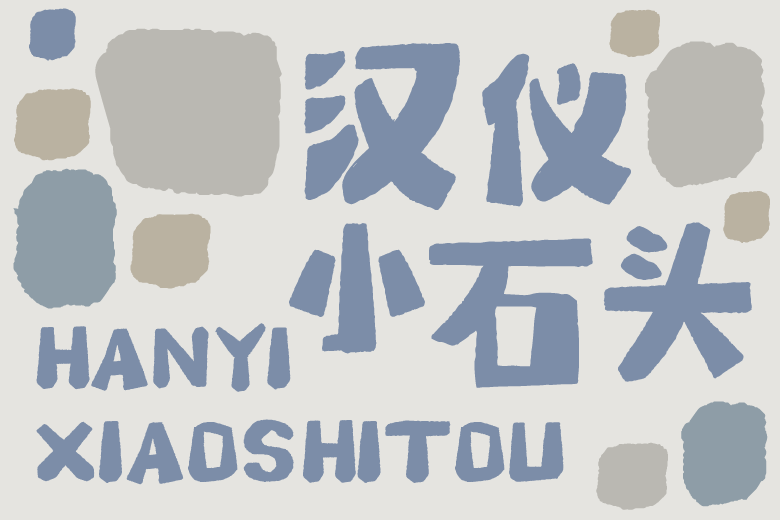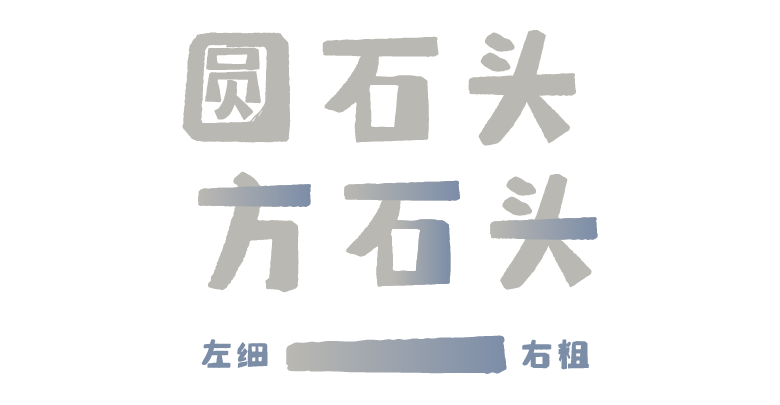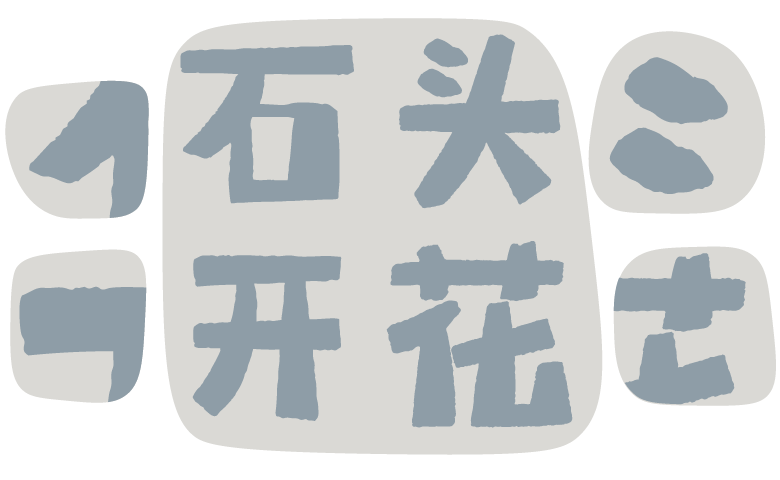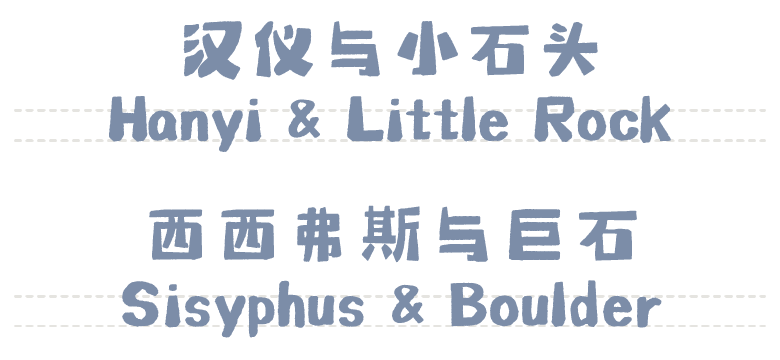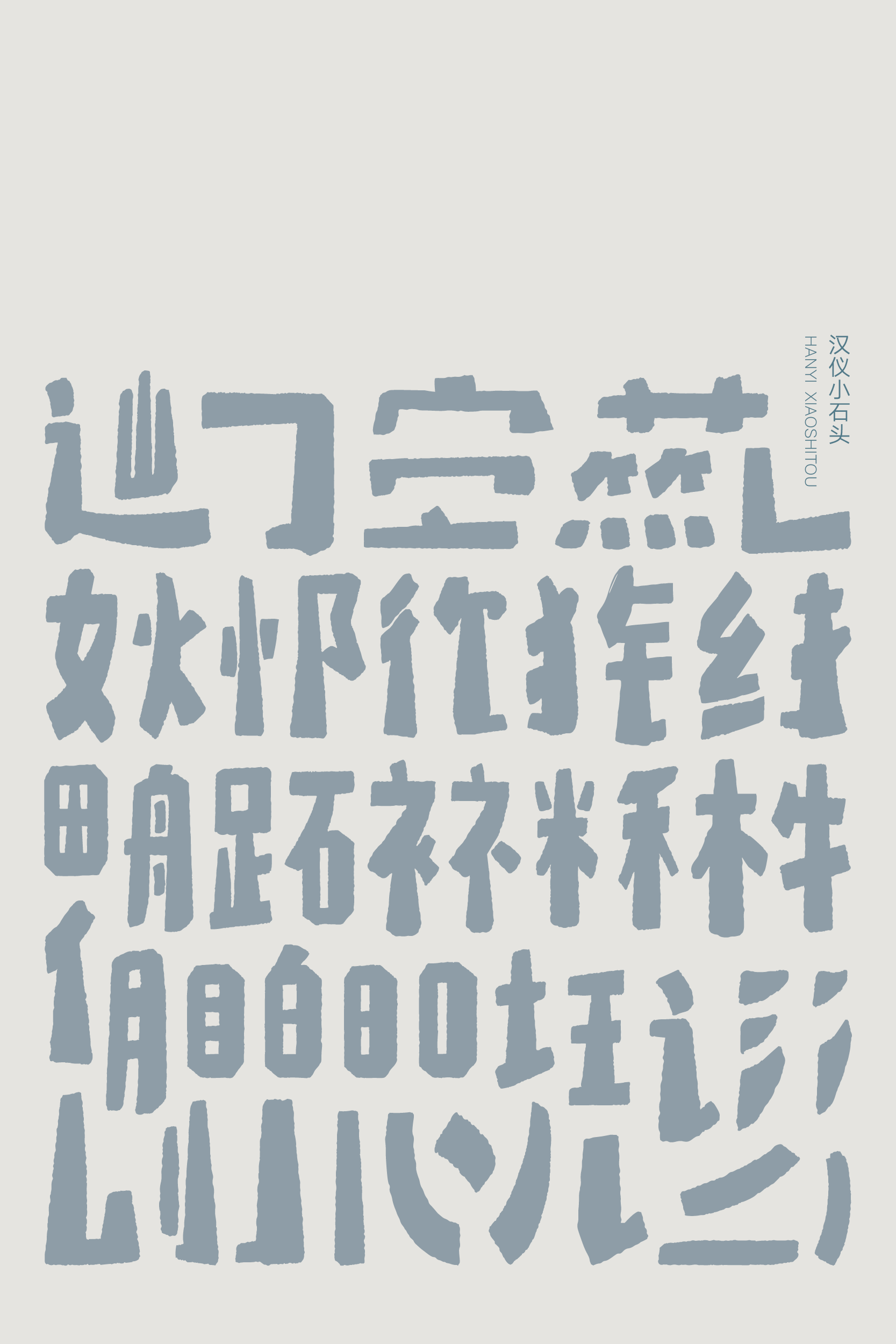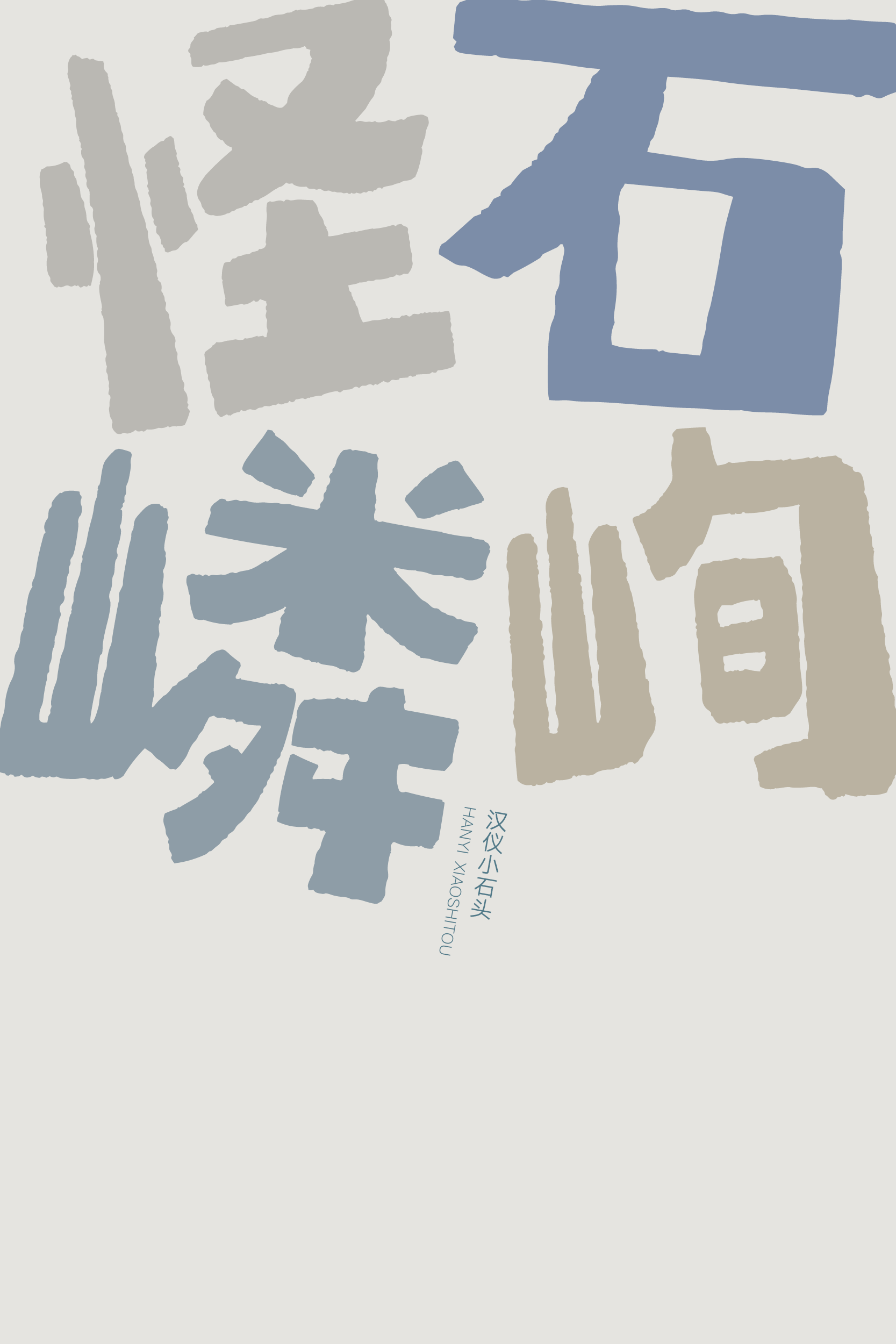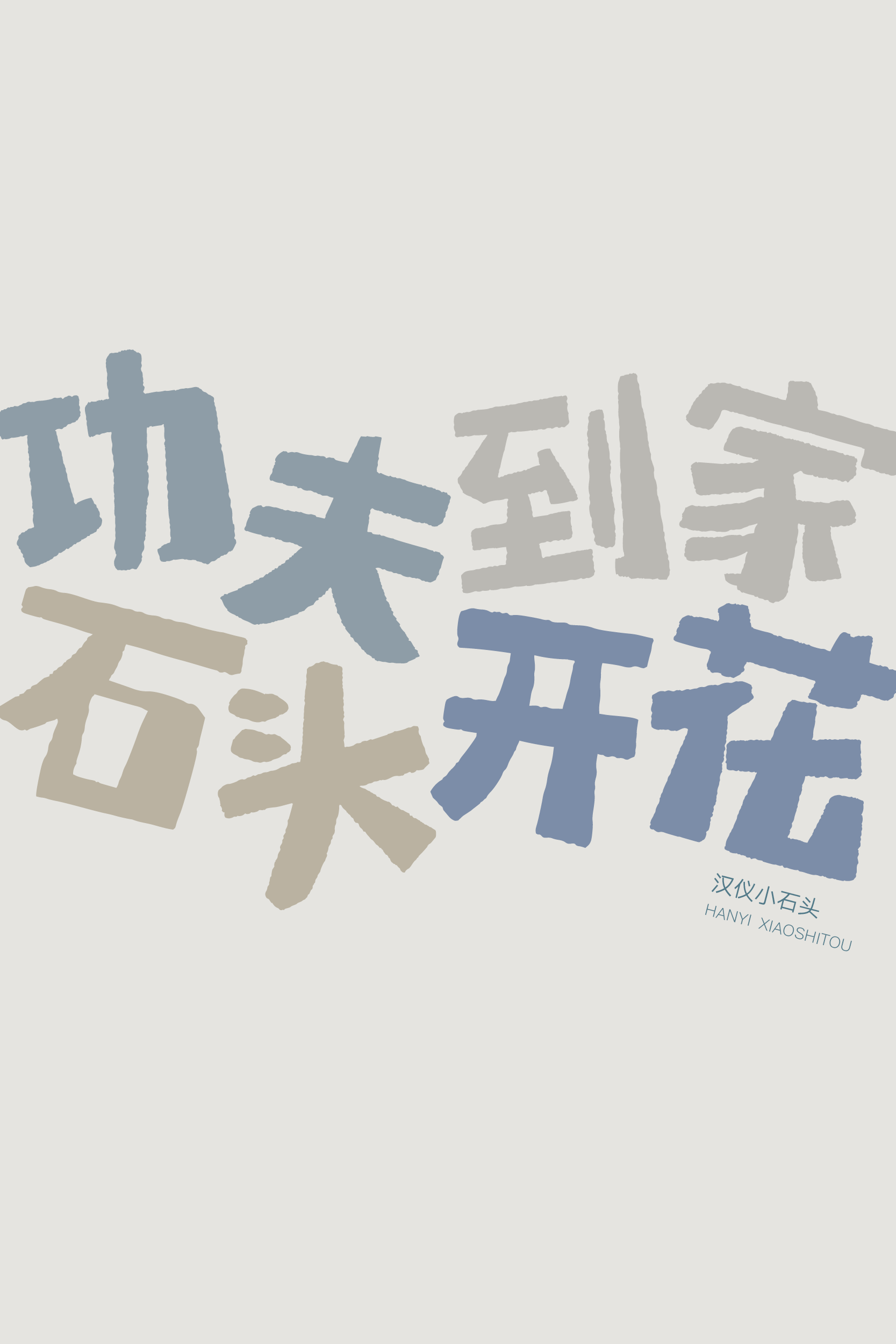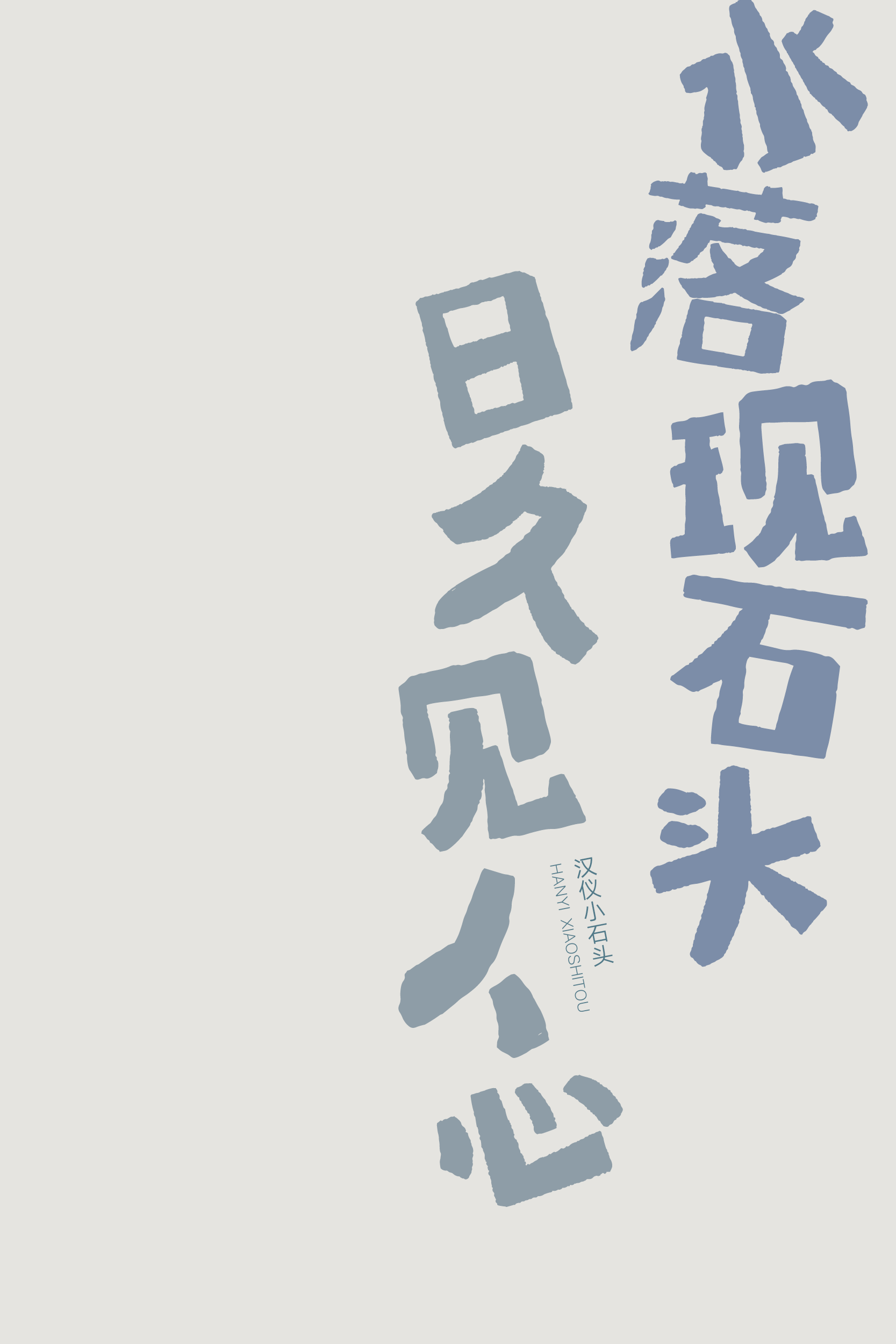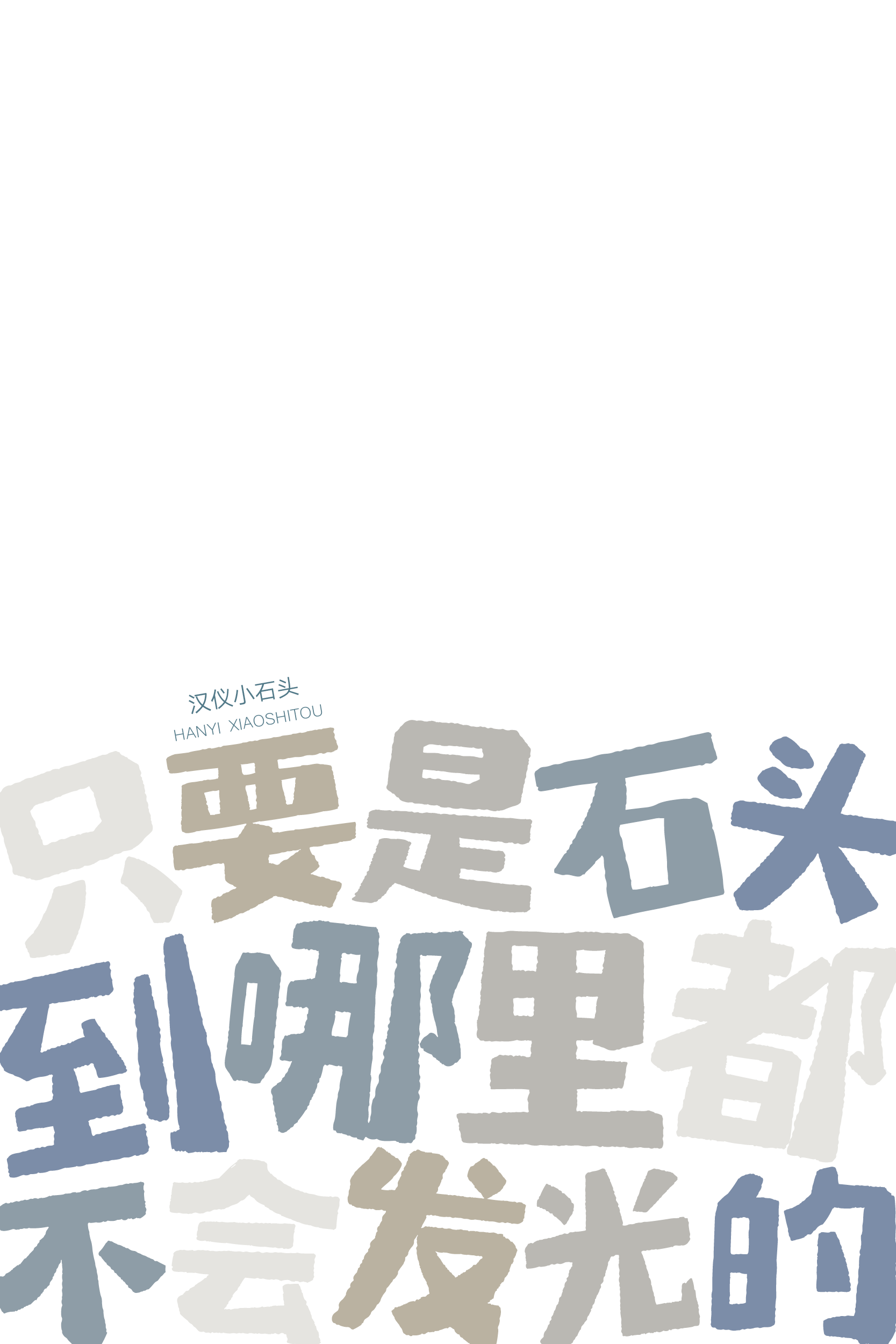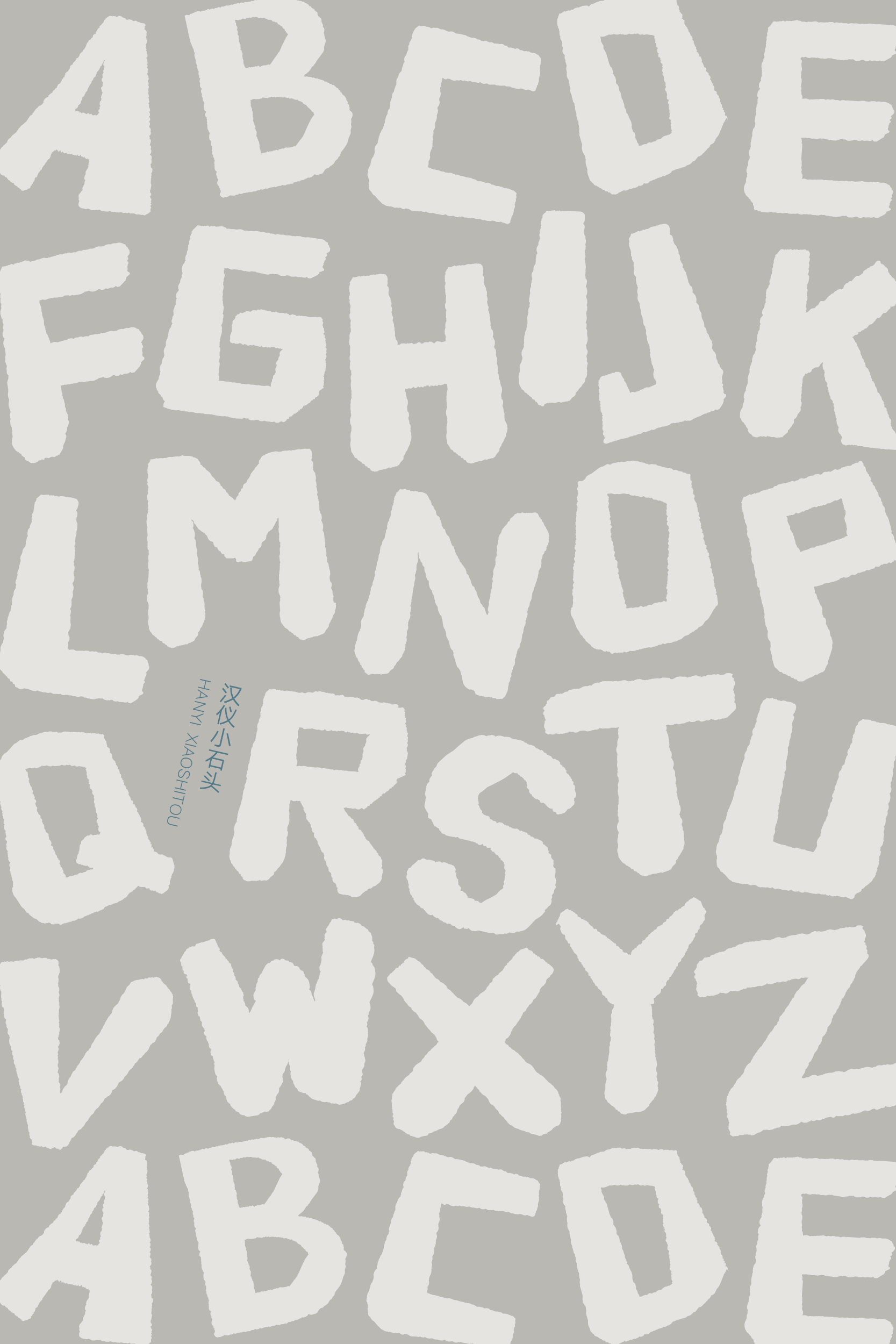
汉仪小石头字体介绍,一款轻松有趣的手写字体
汉仪小石头是由汉仪字库签约作者闫鹏创作的一款轻松有趣的手写字体。这款朴拙可爱的字体设计生动有趣、不拘一格,适合作为标题字体应用于广告标语、游戏动漫、影视综艺、品牌包装等多种场景,与少儿类、儿童类主题十分相宜。
这款字体对字体结构进行了适当的夸张,字面大小形态各异,像路边堆叠的小石头一样高低宽窄略有不同,排版效果生动有趣。
字形上窄下宽,方正之中带着浑圆。
这款字体的整体笔画厚重,保持了左细右粗的设计特点。
起笔和收笔处形成自然的不规则毛边痕迹。
汉仪小石头的西文设计保留了中文设计的整体风格,上窄下宽平稳地立在基线上。中西文搭配和谐,浑然一体。